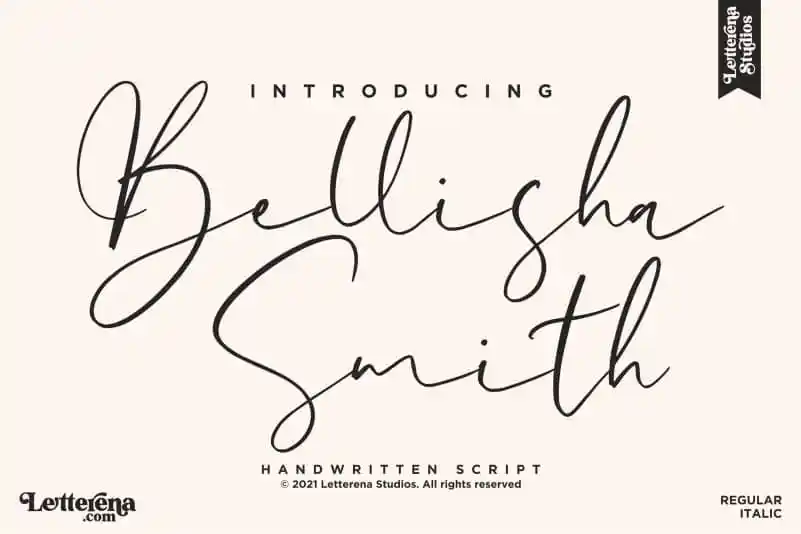
Bellisha Smith Script Font – Download Grátis
A Bellisha Smith Script Font é uma elegante fonte de estilo romântico de calligrafia, ideal para projetos variados como logomarcas, criação de marcas, designs de móveis de casa, embalagens de produtos, taças, frases, cartazes, sacolas de presente, camisetas personalizadas, capas de livro, cartões de nome, convites, cartões de agradecimento e etiquetas. Além disso, é perfeita para projetos que exigem uma assinatura script sofisticada, como capas de livros, identidades visuais e outros materiais de alta qualidade. Com sua aparência fluida e delicada, essa fonte será um elemento adicional de luxo para qualquer projeto visual ou tipográfico em seu portfólio. Designer por Letterenastudios, a Bellisha Smith Script Font é uma escolha perfeita para aqueles que buscam um toque de sofisticação e personalidade em seus trabalhos gráficos.